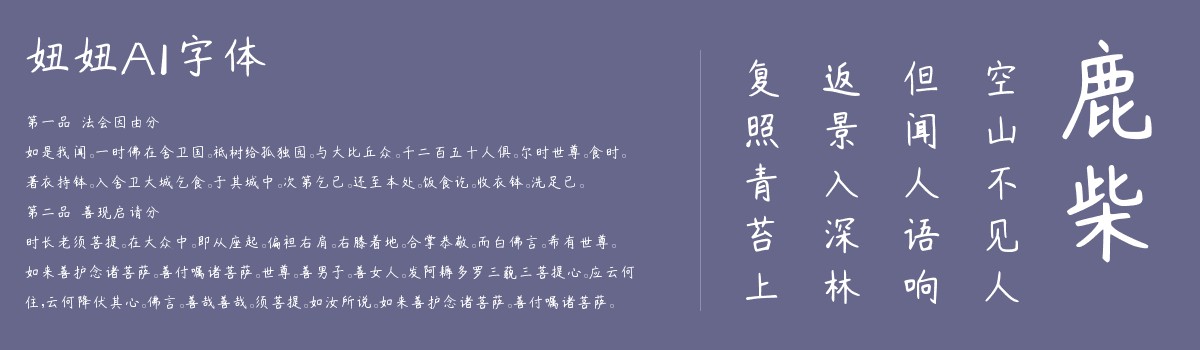
妞妞AI字体是由字体家AI神笔造字网站特别定制的一套免费商用字库,为庆祝妞妞的生日而诞生。这套字体展现了AI技术的创造力和温暖,融合了创意与特别的关怀。每一个字符都充满独特的个性和设计感,适合用于各种场合,为文字增添趣味和独特性。妞妞AI字体背后蕴含着对妞妞和吴菊萍的真诚祝福与关爱之情,希望能陪伴着妞妞成长,传递温暖和正能量。无论是在设计作品中还是日常应用中,妞妞AI字体都能为您带来别具一格的体验和视觉享受。让我们一起用这份特别的礼物,共同感受AI技术与人性的结合,传递爱与温暖的力量。
"温馨定制:AI神笔造字为妞妞打造专属字库,太极禅苑院长陈伟见证生日庆典"
AI神笔造字的创意礼物:
今年,在妞妞生日即将来临之际,字体家AI神笔造字也特别定制了一套免费商用字库作为妞妞的生日礼物。这份特别的礼物不仅展现出了AI技术的创造力,更传递着对妞妞和吴菊萍的祝福和关爱之情。
关于妞妞AI字体
字体家AI神笔造字创始人叶根友表示:“在这个特别的日子里,通过AI技术与人情温暖的结合,我们为妞妞定制了这套专属字库,希望能传递我们对她的祝福与关怀。愿这份特别的礼物带来更多的创意与温暖,陪伴着妞妞成长。”